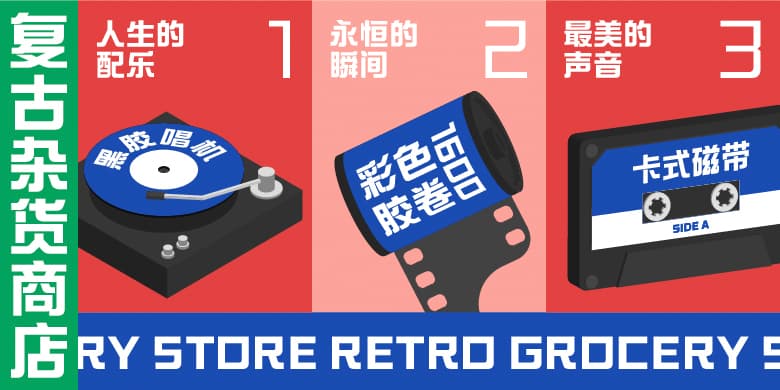
方正新综艺黑家族
综艺体由郭炳权老师创作于上世纪70年代,与英文字体“Helvetica”有异曲同工之妙,至今仍受大众所喜欢,新综艺黑沿用综艺体部分特征,结合更舒适的视觉效果对相关笔画进行了再度的修改使其整体感觉更加的舒畅灵动,整体字形端正平稳,结构简洁大方,新综艺黑共有11个字重,更加的适合运用于各类场合及品牌宣传推广,是一款实用的字体。